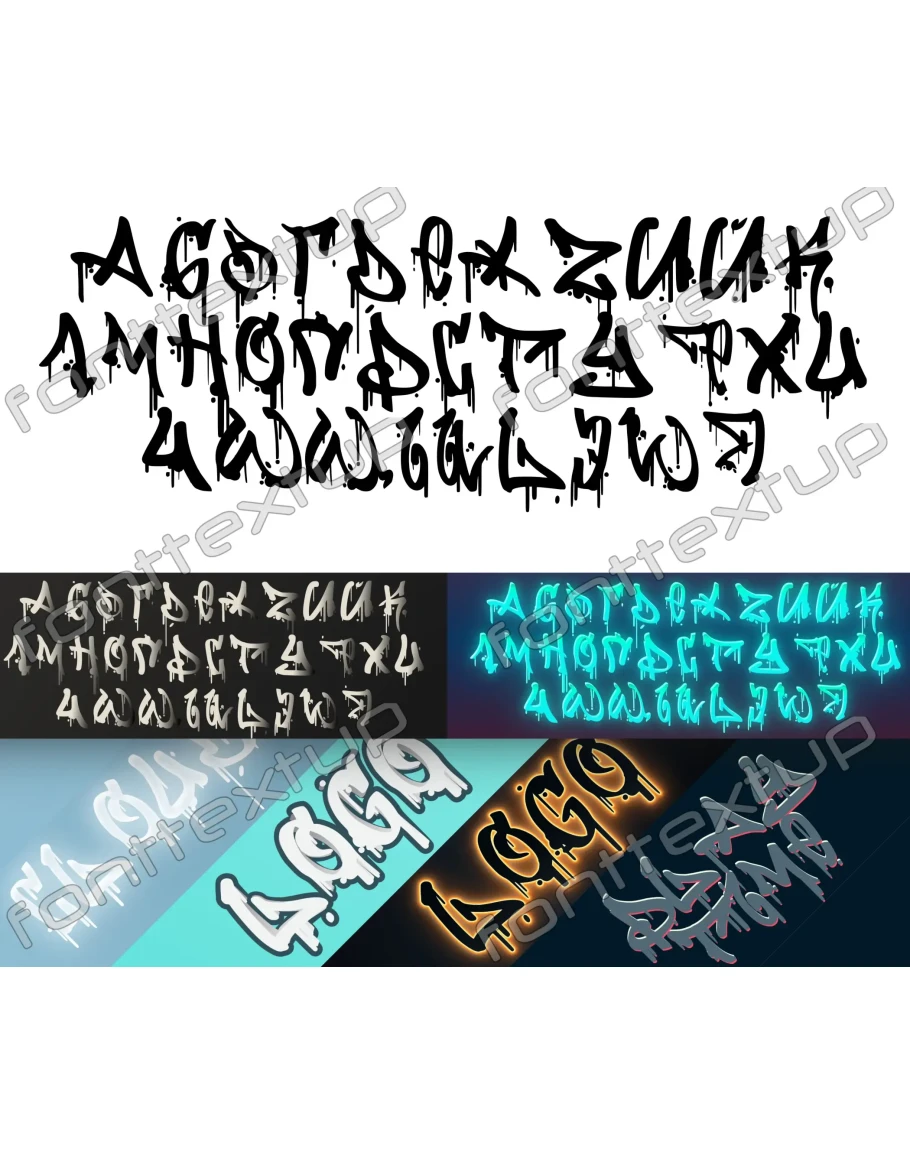
• Кириллический граффити шрифт
Кириллический граффити шрифт - это дерзкий и стильный шрифт, созданный вдохновением уличной граффити-культуры. Он сочетает в себе традиционные кириллические буквы с элементами современного искусства и граффити-стиля, что делает его идеальным выбором для дизайна логотипов, заголовков, постеров, флаеров и других элементов графического дизайна. Скачать кириллический граффити шрифт - значит получить возможность выразить свою индивидуальность и добавить уличный стиль в свои проекты.
Кириллический граффити шрифт